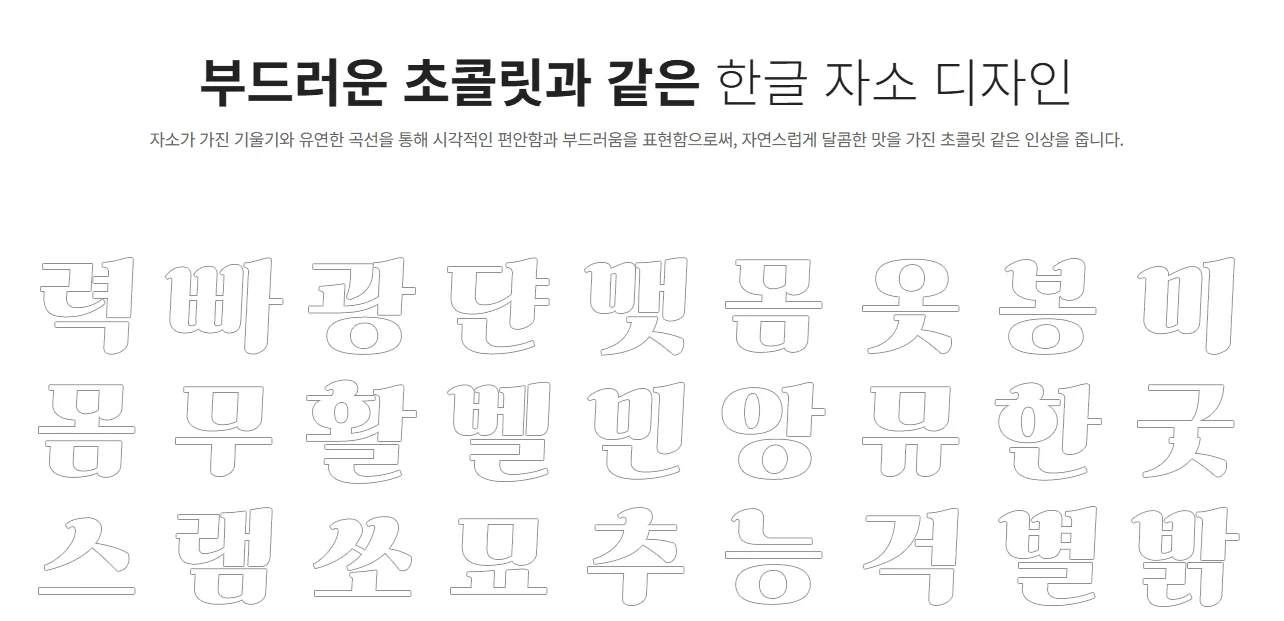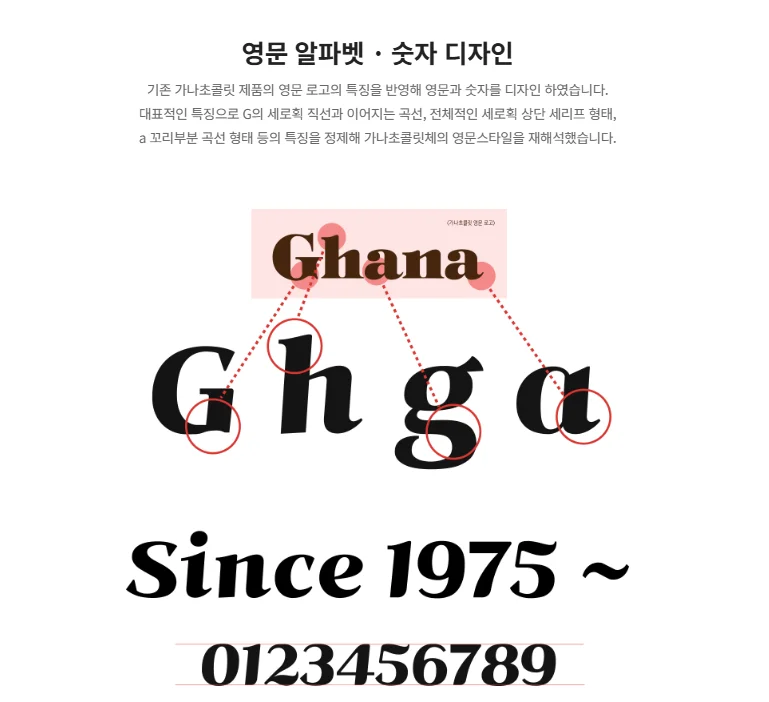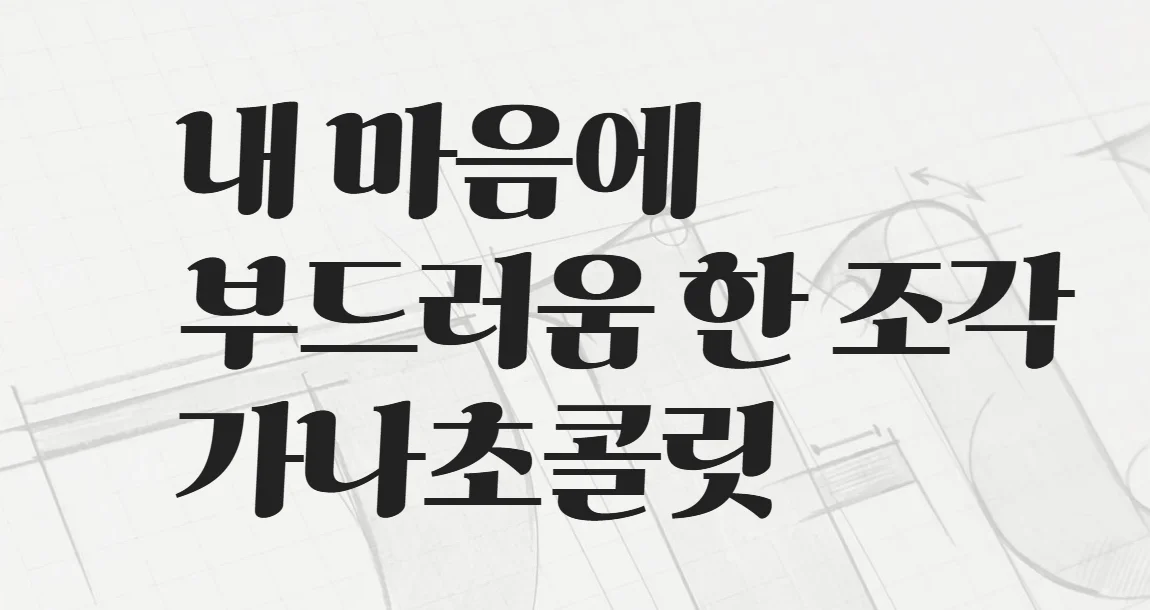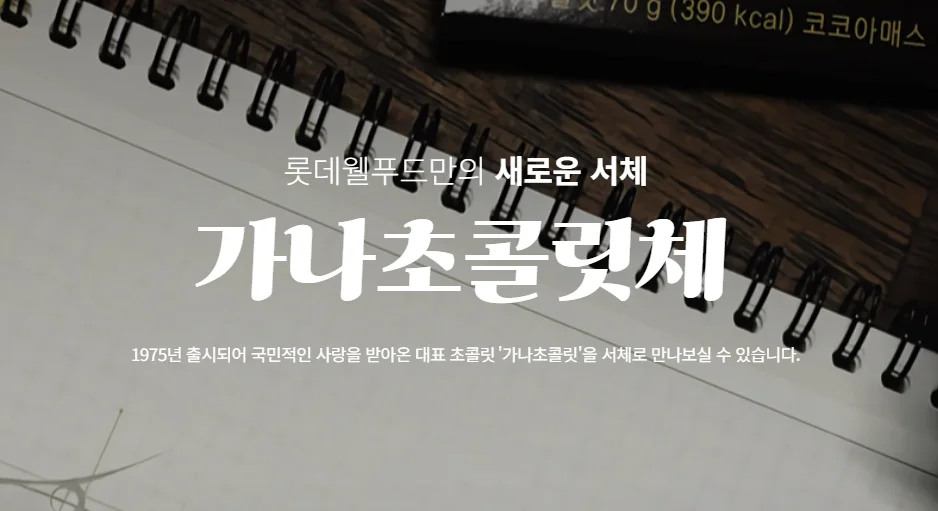
🍫 1. 가나초콜릿체란?
가나초콜릿체는 롯데제과(현 롯데웰푸드)가 2020년 2월 7일 밸런타인데이를 기념해 공식 배포한 무료 한글 서체입니다. 1975년 출시 이후 국민 초콜릿으로 자리 잡은 가나초콜릿의 부드럽고 달콤한 브랜드 이미지를 글꼴 디자인에 그대로 담아낸 것이 특징입니다.
기업 브랜드가 자사 제품의 감성을 폰트로 표현해 대중에게 무료 배포한 사례로, 빙그레체, 배민 주아체, 롯데리아 찹쌀떡체 등과 함께 브랜드 무료 폰트의 대표 사례로 손꼽힙니다.
| 제작·배포 | 롯데제과(현 롯데웰푸드) |
| 출시일 | 2020년 2월 7일 |
| 서체 분류 | 세리프(Serif) 계열 |
| 제공 굵기 | Regular 단일 웨이트 |
✨ 2. 가나초콜릿체 디자인 특징
가나초콜릿체가 다른 무료 폰트와 구별되는 핵심 디자인 요소는 총 5가지입니다.
① 약 3도의 미세한 기울기
가나초콜릿체의 가장 두드러지는 특징은 글자 전체에 적용된 약 3도의 미세한 기울기입니다. 일반 정체(正體)와는 달리 살짝 기울어진 구조가 글자에 경쾌함과 주목성을 부여합니다. 일반 이탤릭체처럼 과하게 기울지 않기 때문에 가독성을 유지하면서도 생동감 있는 느낌을 줍니다.
② 곡선 중심의 자형 설계
가나초콜릿체는 직선이 들어갈 자리에 의도적으로 부드러운 곡선을 배치했습니다. 가나 초콜릿을 한 입 베어 물었을 때의 부드럽고 달콤한 느낌을 시각적으로 표현한 것입니다. 각진 서체에서 느껴지는 딱딱함이 없고, 보는 것만으로도 편안하고 따뜻한 감정을 유발합니다.
③ 경량 세리프(Light Serif) 스타일
가나초콜릿체는 세리프 계열이지만 명조체처럼 무겁거나 고풍스럽지 않습니다. 가벼운 세리프 처리 덕분에 현대적이면서도 우아한 인상을 동시에 줍니다. 레트로 감성을 원하면서도 너무 올드한 느낌은 피하고 싶을 때 최적의 선택입니다.
④ 타이틀·헤드라인 최적화 굵기
Regular 단일 굵기만 제공되는데, 이 굵기 자체가 타이틀, 헤드라인, 강조 문구에 딱 맞는 무게감입니다. 본문 장문 텍스트보다는 짧고 임팩트 있는 한 줄 문구, 포스터 제목, 배너 카피, 유튜브 썸네일 텍스트에 활용할 때 진가를 발휘합니다.
⑤ 가나 브랜드 아이덴티티 반영
영문 'Ghana' 로고의 시각적 특성을 한글 자형에 녹여냈습니다. 판 초콜릿을 손으로 부러뜨릴 때의 경쾌한 감각, 그리고 초콜릿 특유의 달콤하고 부드러운 질감이 글자 하나하나에 담겨 있습니다. 단순한 폰트가 아니라 브랜드의 감성을 시각적으로 전달하는 커뮤니케이션 도구로 설계된 서체입니다.
- 약 3도 기울기 + 곡선 자형 + 경량 세리프의 부드럽고 달콤한 디자인